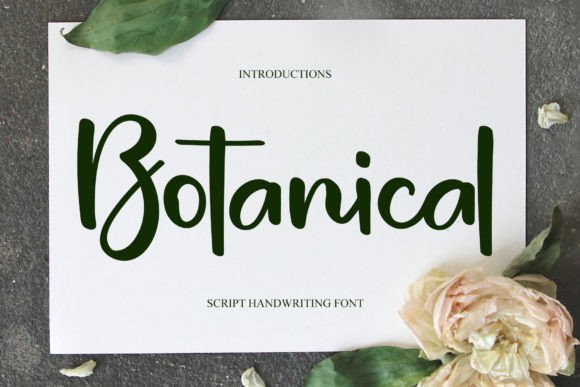
Botanical
Encontrar os elementos de design certos pode ser um desafio, mas Botanical oferece uma coleção excepcional que eleva o seu trabalho instantaneamente.
Quer você esteja criando produtos POD (Print on Demand), convites de casamento ou gráficos para mídias sociais, Botanical é a escolha ideal.